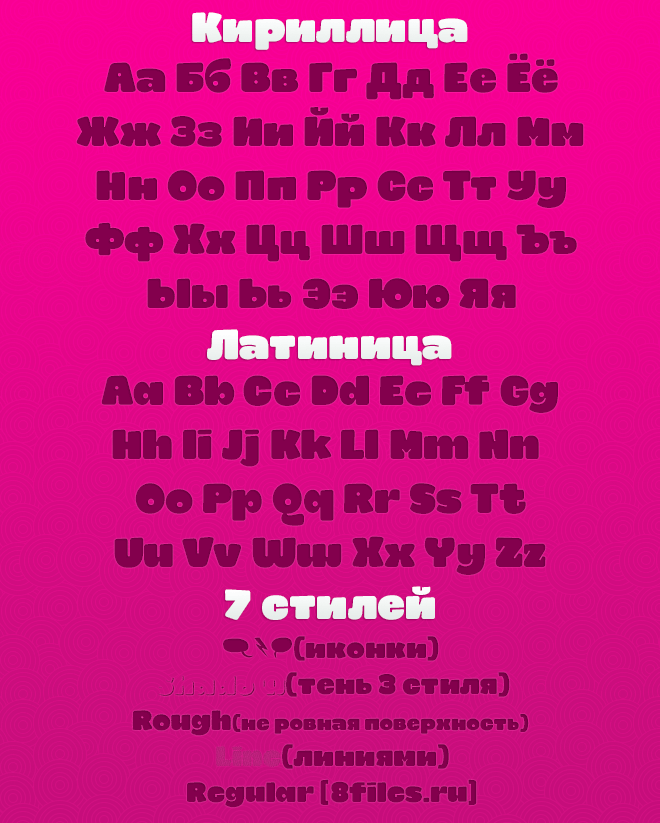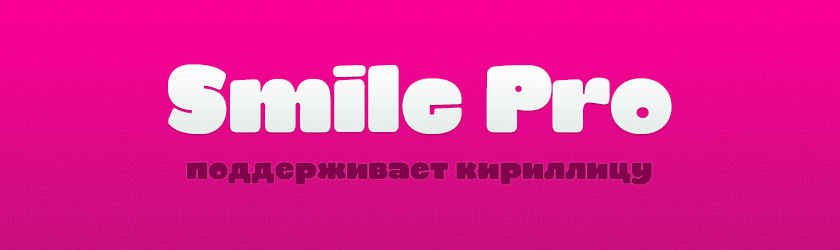
Font (шрифт) Smile Pro
Представляю вашему вниманию красивый шрифт (font) Smile Pro. Шрифт имеет 7 стилей и поддержку Кириллицы. Скачай Smile Pro и используй в личных нуждах.